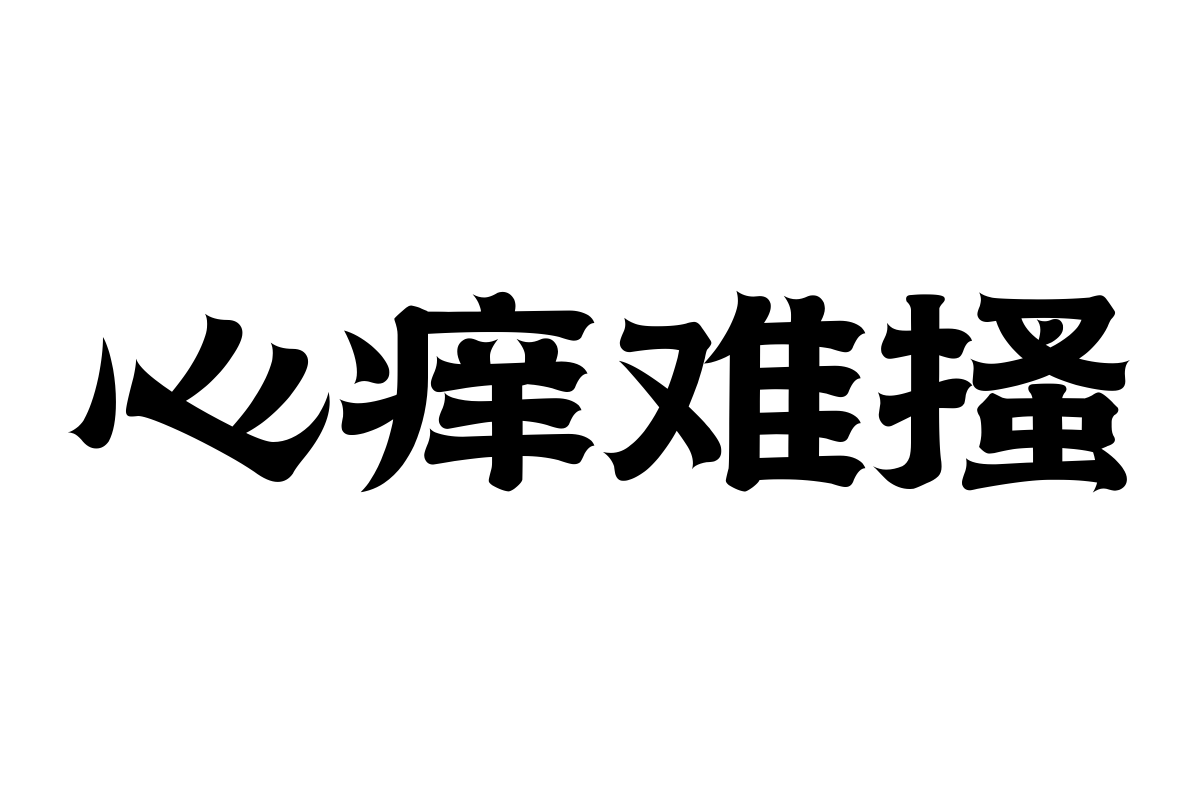
上首万福体是一种书法字体,它的特点是笔画流畅,结构严谨,字形端正。这种字体适合用于书写对联、横幅等装饰性文字,给人一种庄重、喜庆的感觉。
上首万福体的笔画粗细适中,既有力度又不失柔美。它的结构严谨,每个字的笔画都经过精心设计,使得整体看起来既美观又富有艺术感。同时,这种字体也具有一定的可读性,即使长时间阅读也不会感到疲劳。
总的来说,上首万福体是一种非常适合用于节日装饰和庆祝活动的书法字体。